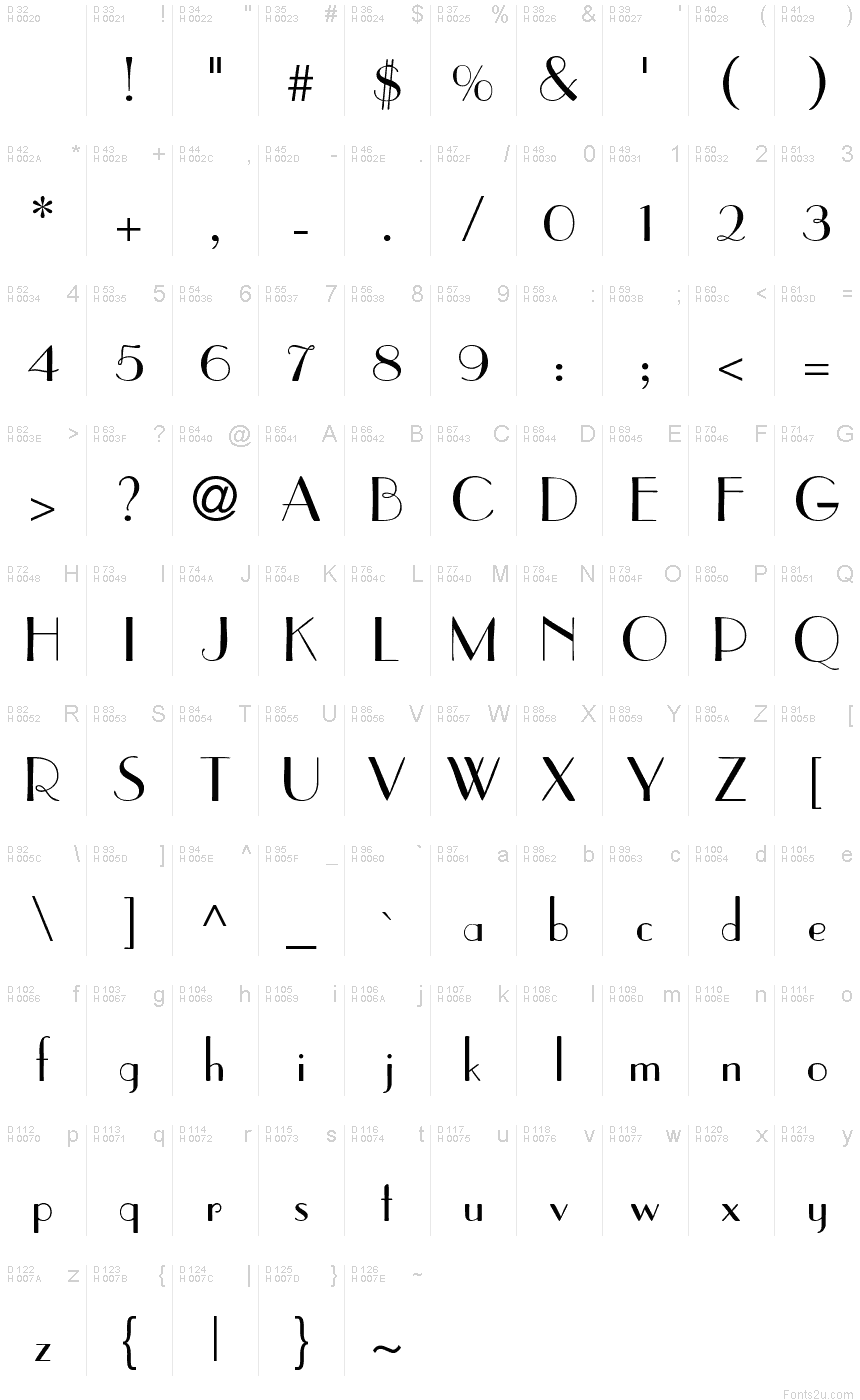
DeusenburgSSK
Deusenburg SSK od Southern Software to darmowy, szeryfowy krój pisma w stylu retro, który przywołuje blask epoki Art Déco. Litery są wysokie i smukłe, z eleganckimi krzywiznami i niezwykle cienkimi liniami, które wyglądają, jakby zostały nakreślone piórem na błyszczącym papierze. Odstępy są przestronne, lecz przemyślane, nadając każdemu słowu pełen gracji, wydłużony wygląd, który przyciąga wzrok, nie narzucając się.
Z Deusenburg SSK zyskujesz stylowe narzędzie do projektowania identyfikacji wizualnych koktajl-barów, plakatów w stylu vintage, okładek książek, opakowań butikowych, zaproszeń czy nagłówków czasopism. Ten darmowy font najlepiej prezentuje się w większych rozmiarach, gdzie jego wyrafinowane kształty i subtelne kontrasty mogą w pełni wybrzmieć; połącz go z prostym, geometrycznym bezszeryfowym krojem w tekście głównym, aby zachować przejrzysty układ, podczas gdy Deusenburg SSK doda całości charakteru.